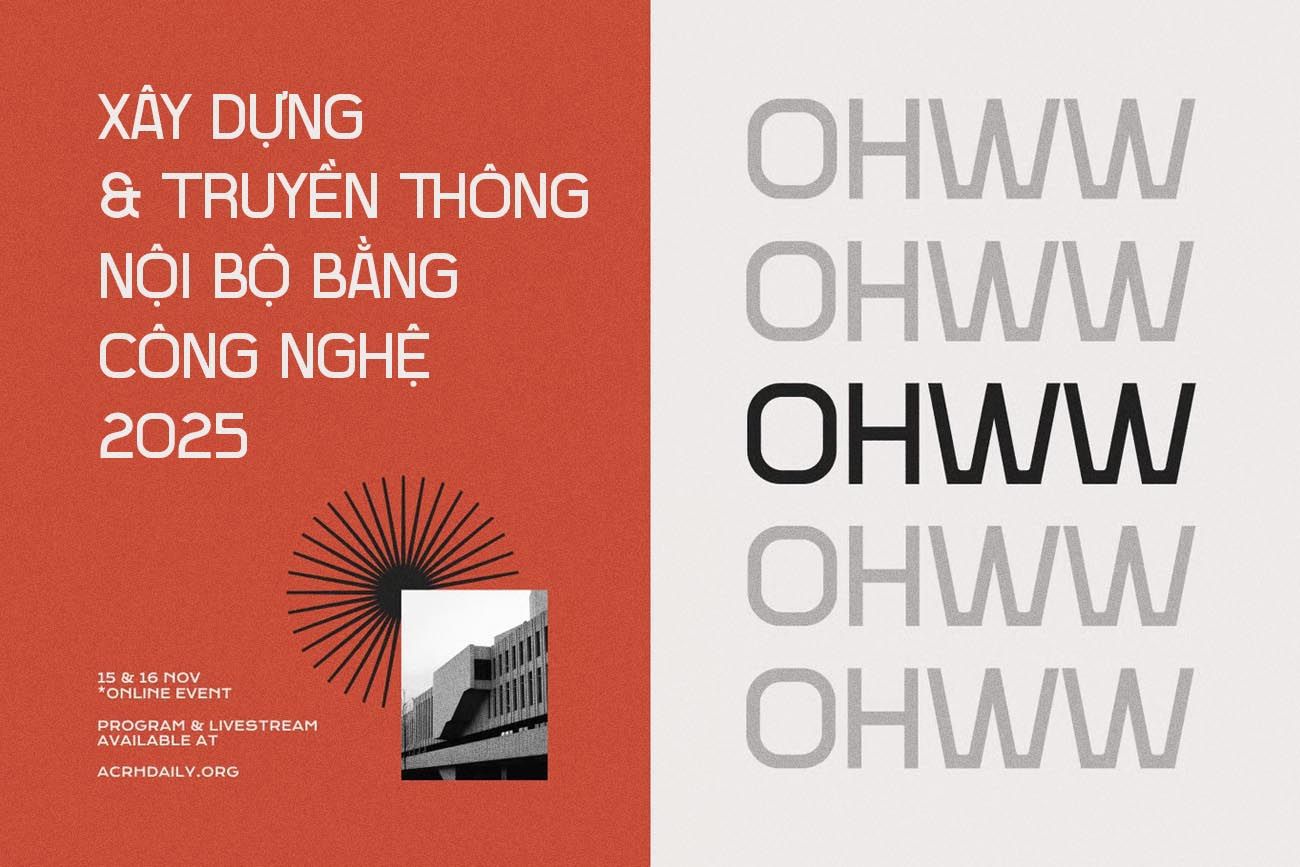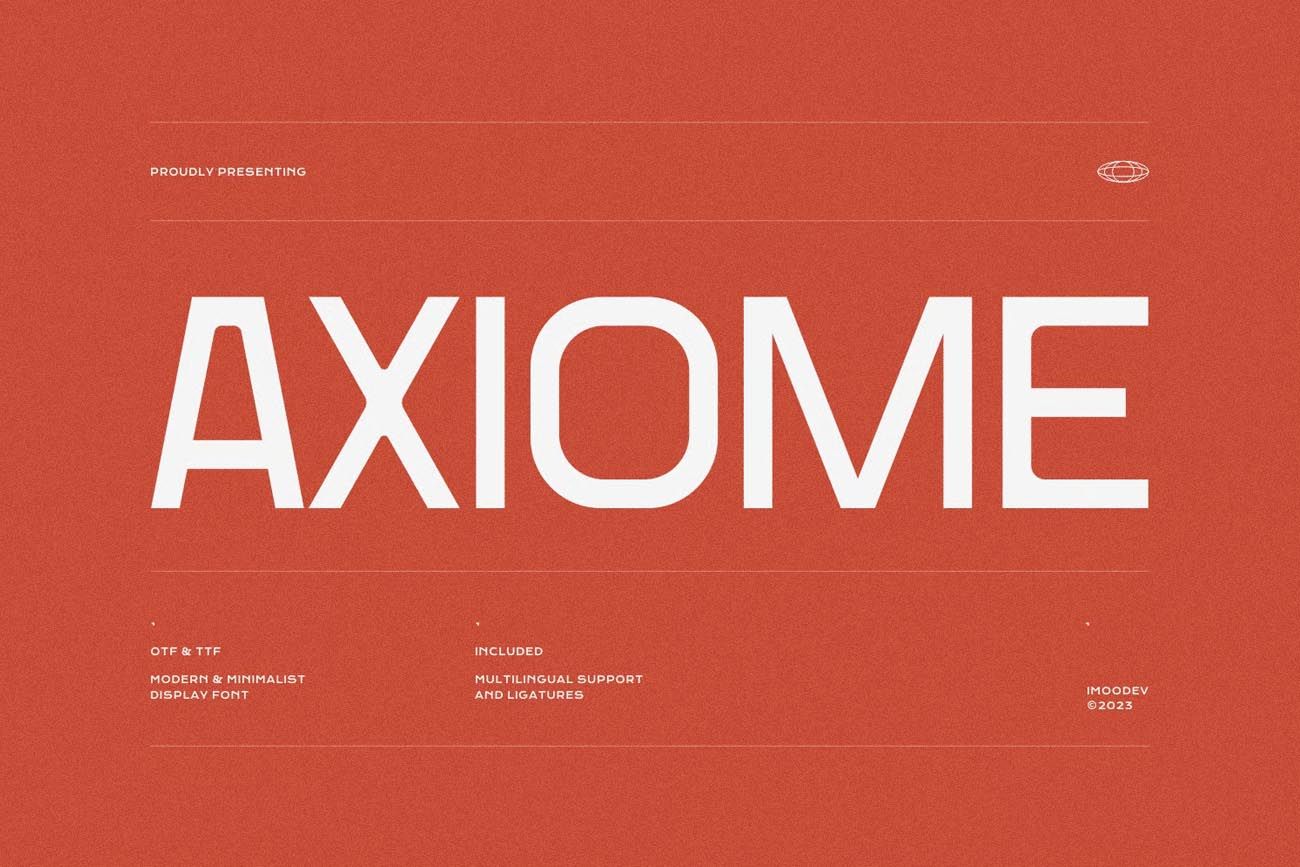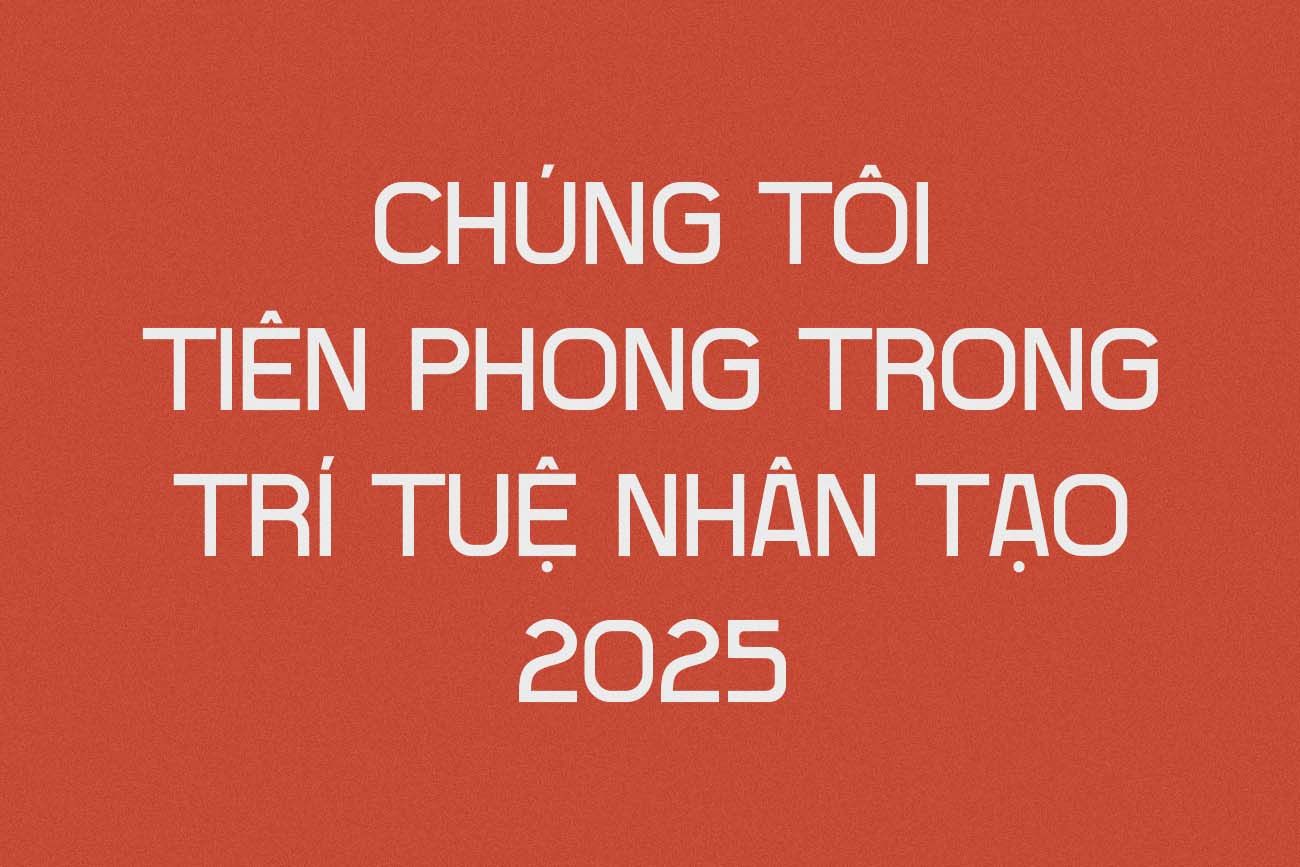
Nếu bạn đang tìm kiếm một font chữ công nghệ hiện đại, đơn giản nhưng vẫn truyền tải rõ ràng sự chuyên nghiệp và mạnh mẽ, thì font chữ Axiome Regular chắc chắn là lựa chọn đáng cân nhắc. Với phong cách geometric sans-serif, kiểu chữ này đang được nhiều nhà thiết kế ưa chuộng trong năm 2025 nhờ sự sắc sảo, tối giản và dễ ứng dụng trong đa dạng bối cảnh thiết kế.
TH Axiome Regular là một font chữ không chân (sans-serif) được thiết kế bởi Jean-Baptiste Morizot và phát hành miễn phí theo giấy phép Open Font License (OFL). Font mang kiểu dáng hình học (geometric) với các đường nét vuông vức, gọn gàng, tỉ lệ cân đối, tạo cảm giác công nghệ, hiện đại và tối ưu hóa trải nghiệm thị giác.
Font chữ này hiện đã có bản Việt hóa đầy đủ, hỗ trợ tiếng Việt có dấu (bao gồm cả Ư, Ừ, Ứ, Ự…), giúp bạn yên tâm sử dụng trong thiết kế tại thị trường Việt Nam mà không lo lỗi font hay dấu lệch.
Thiết kế geometric sắc sảo: Các ký tự đều có trục thẳng, đường cong chuẩn xác, tạo nên vẻ đẹp công nghiệp và logic.
Không chân – Không thừa: Kiểu sans-serif giúp văn bản gọn gàng, mạch lạc và dễ đọc trên mọi kích thước màn hình.
Tương thích tốt với hệ thống thiết kế UI/UX: Font rất phù hợp để sử dụng trong giao diện người dùng, trình bày báo cáo, dashboard, hoặc các trang landing page hiện đại.
Tỷ lệ chữ tối ưu cho trình chiếu: Axiome hiển thị tốt trong thiết kế slide PowerPoint, Keynote và các ấn phẩm truyền thông nội bộ.
Thiết kế thương hiệu công nghệ, startup, phần mềm
Giao diện dashboard, app, web chuẩn UI/UX
Trình chiếu thuyết trình, infographics, báo cáo số liệu
Poster sự kiện hiện đại, truyền thông nội bộ, thiết kế học thuật
Với nét chữ hiện đại, font Axiome Việt hóa mang đến cảm giác chuyên nghiệp mà không quá cứng nhắc – một lựa chọn lý tưởng cho những ai theo đuổi thiết kế tối giản nhưng hiệu quả cao.
Trong thời đại thiết kế lấy người dùng làm trung tâm, việc lựa chọn một font chữ hiện đại như TH Axiome Regular là bước đi đúng đắn để tối ưu hóa trải nghiệm thị giác. Đây chính là font sans-serif đẹp năm 2025 mà bạn nên tải về và đưa vào hệ thống thiết kế của mình.